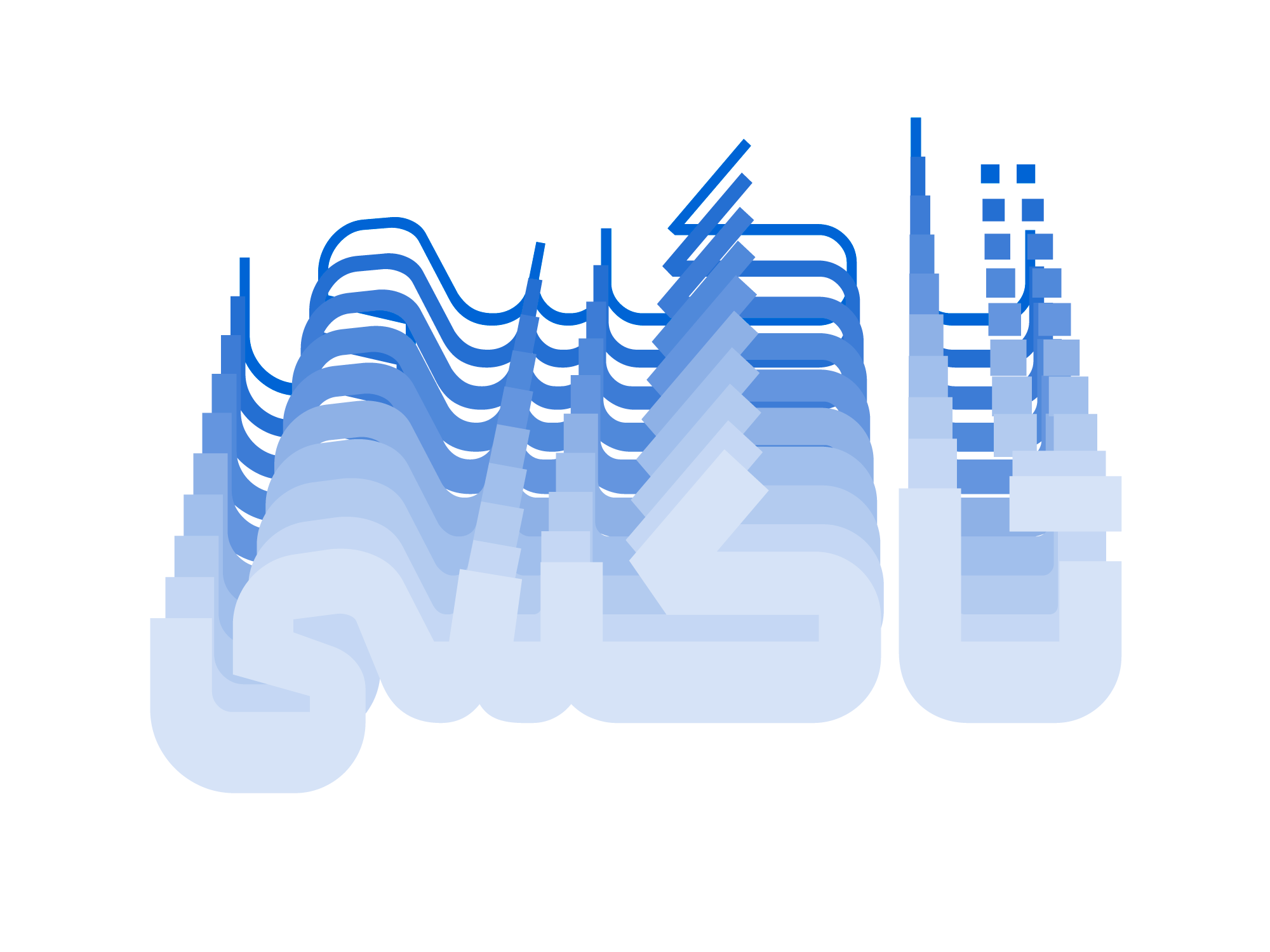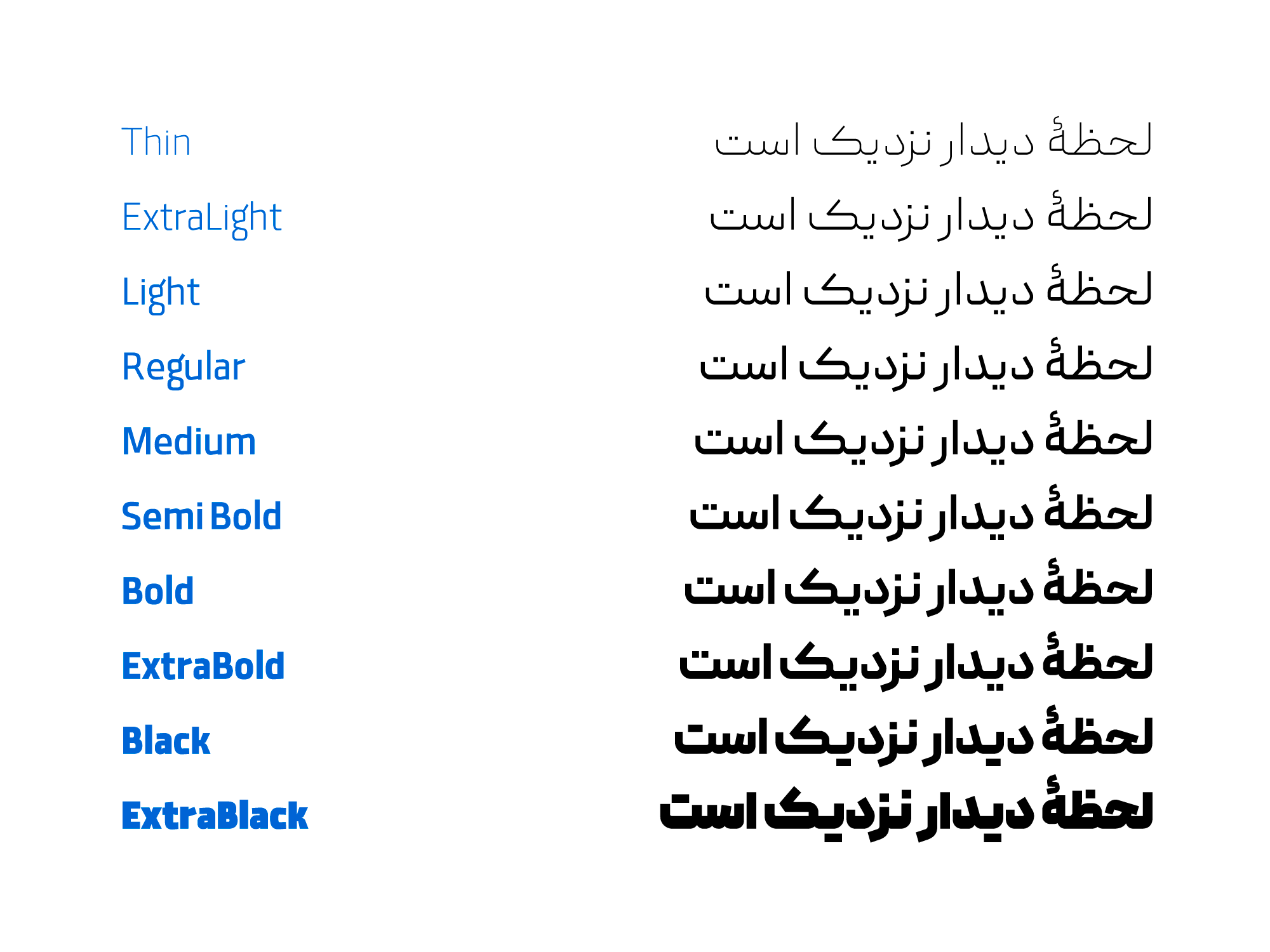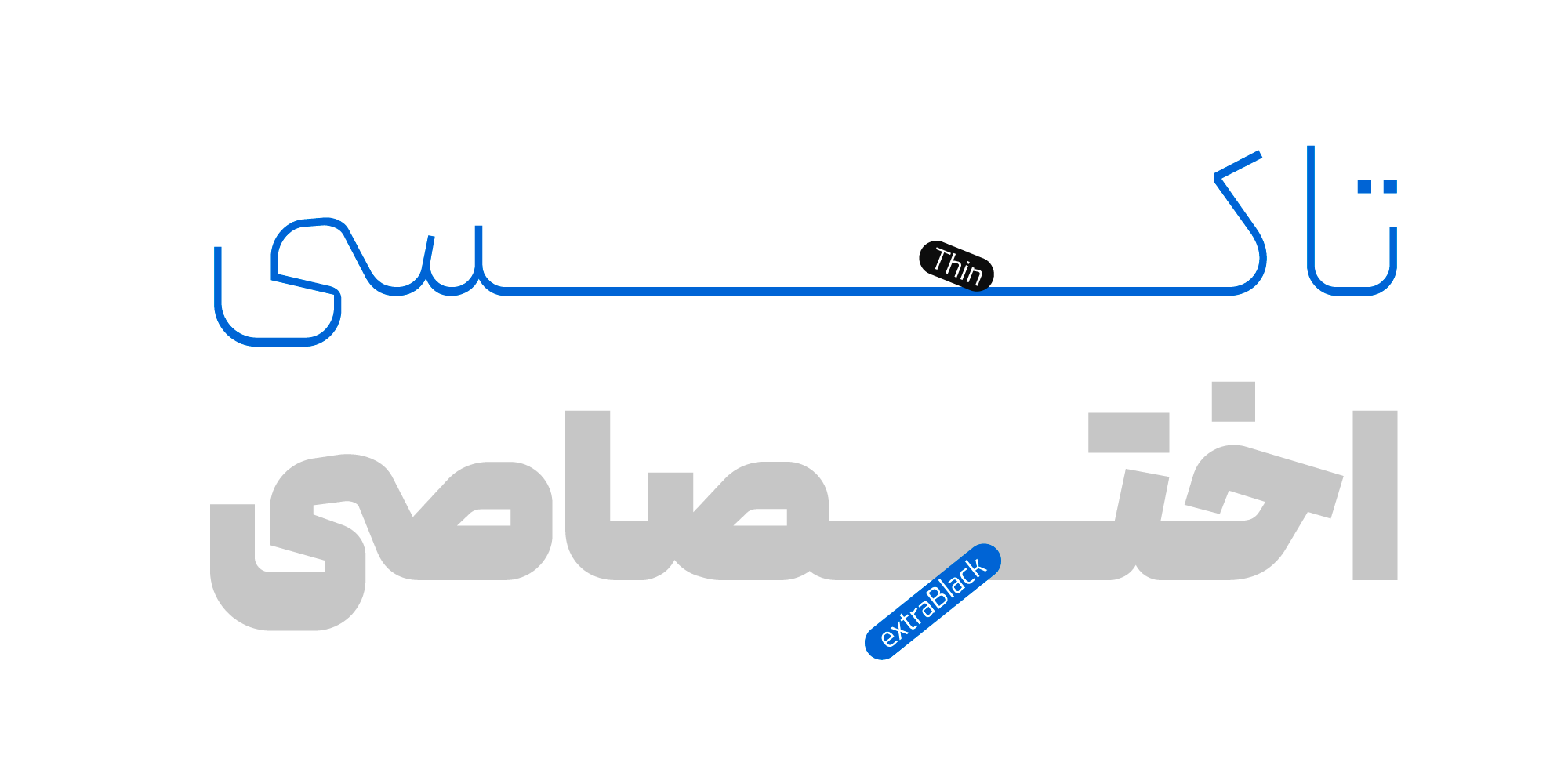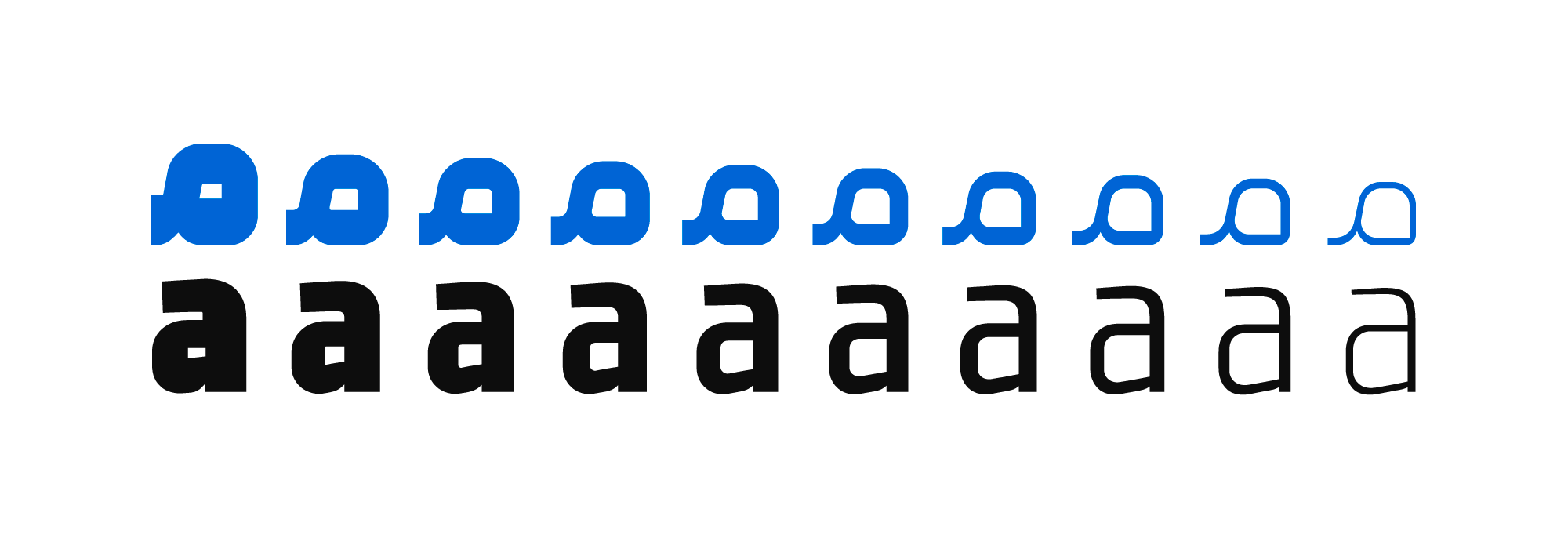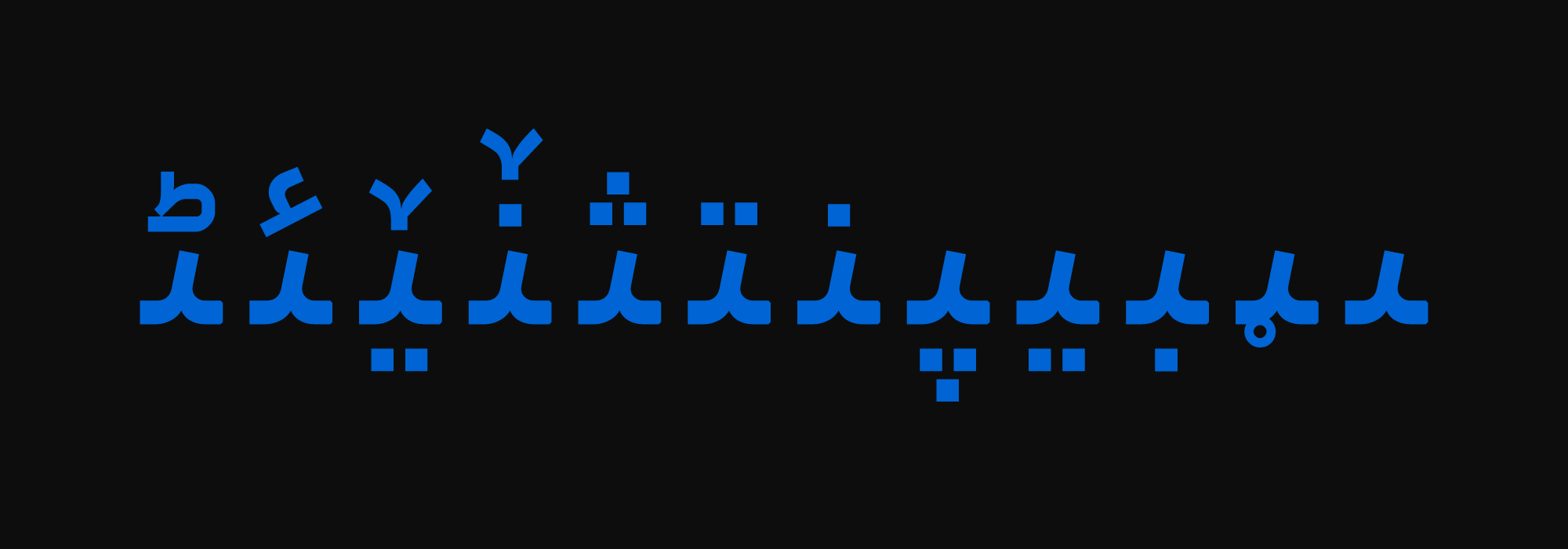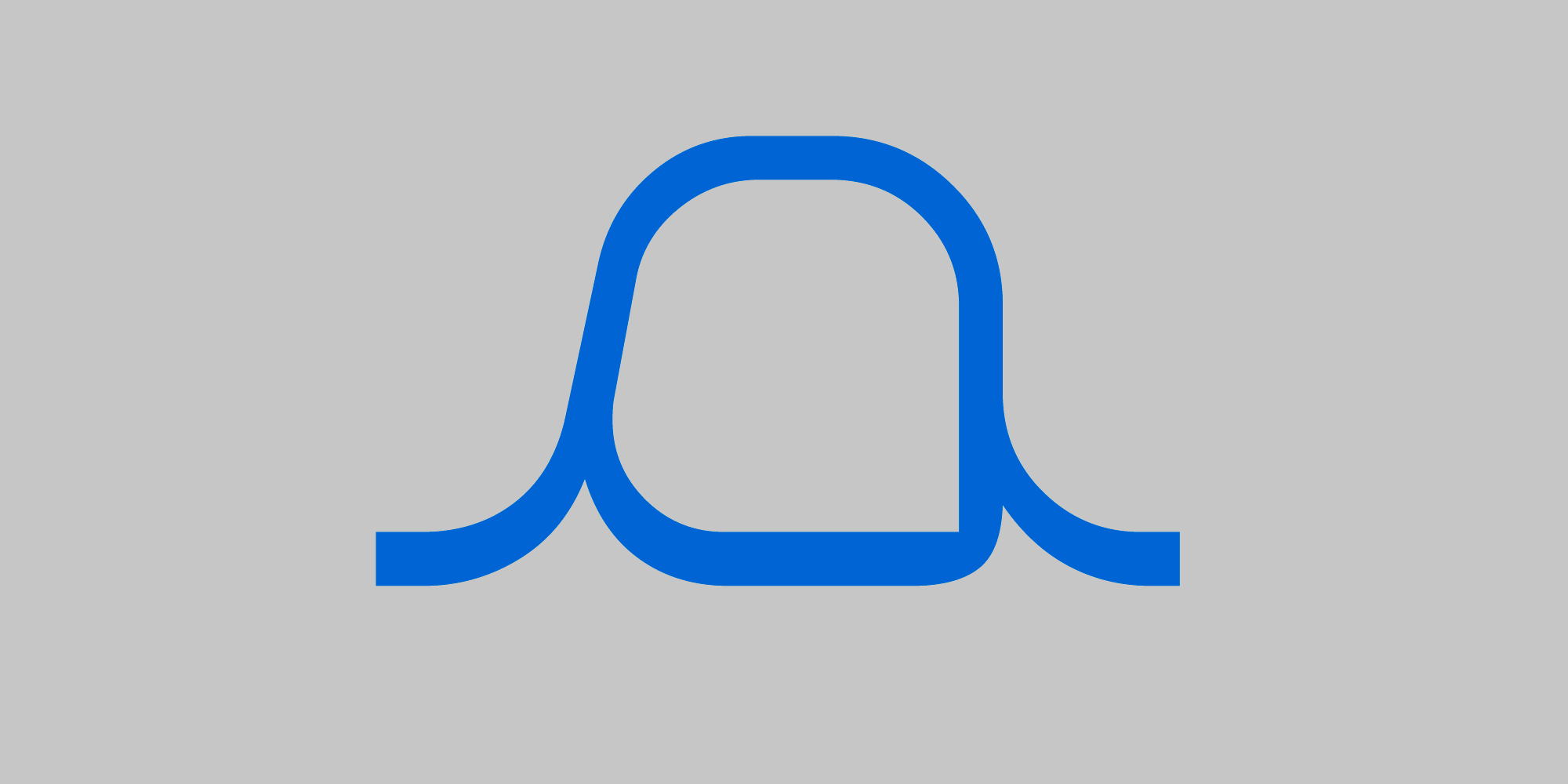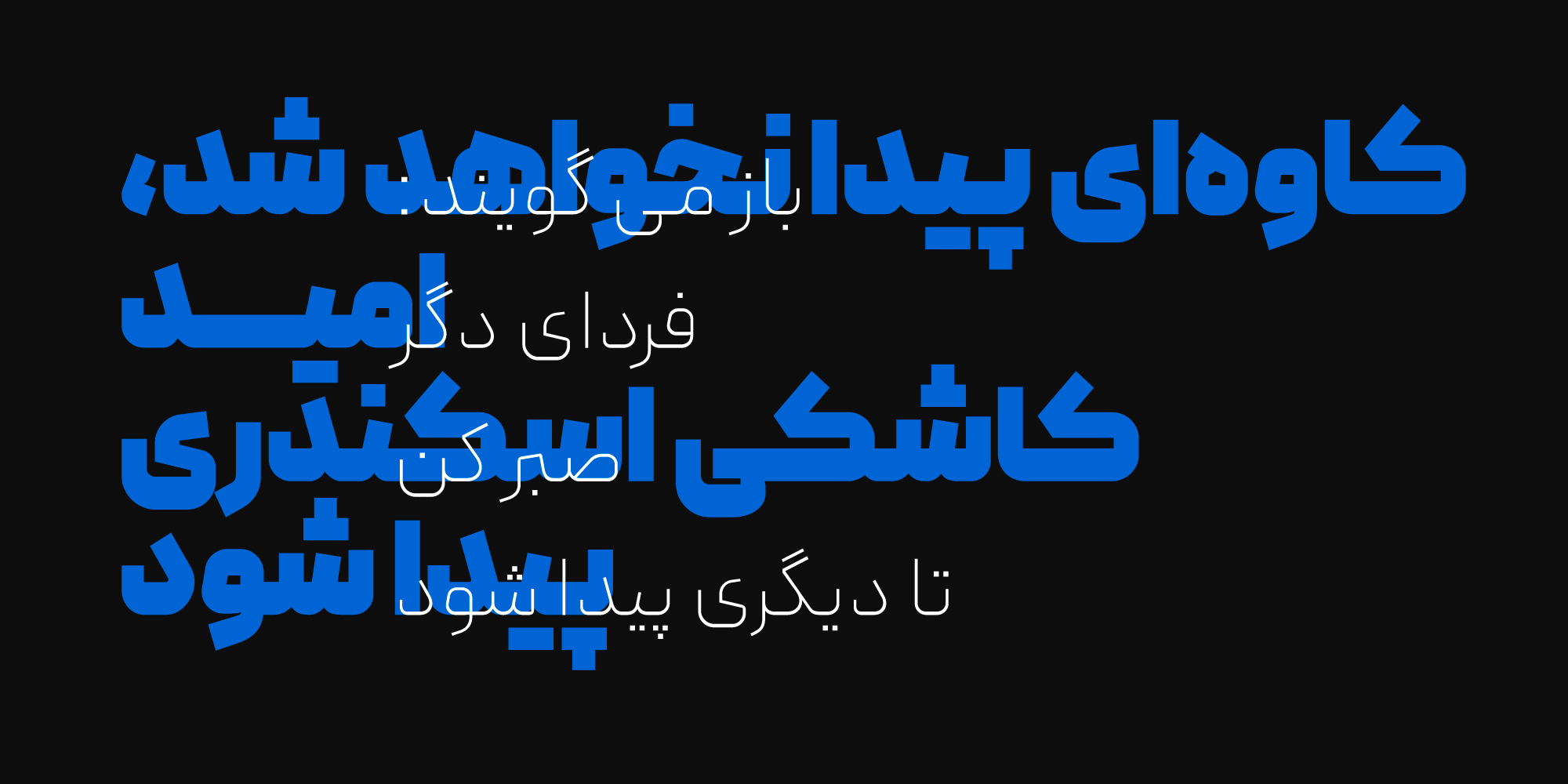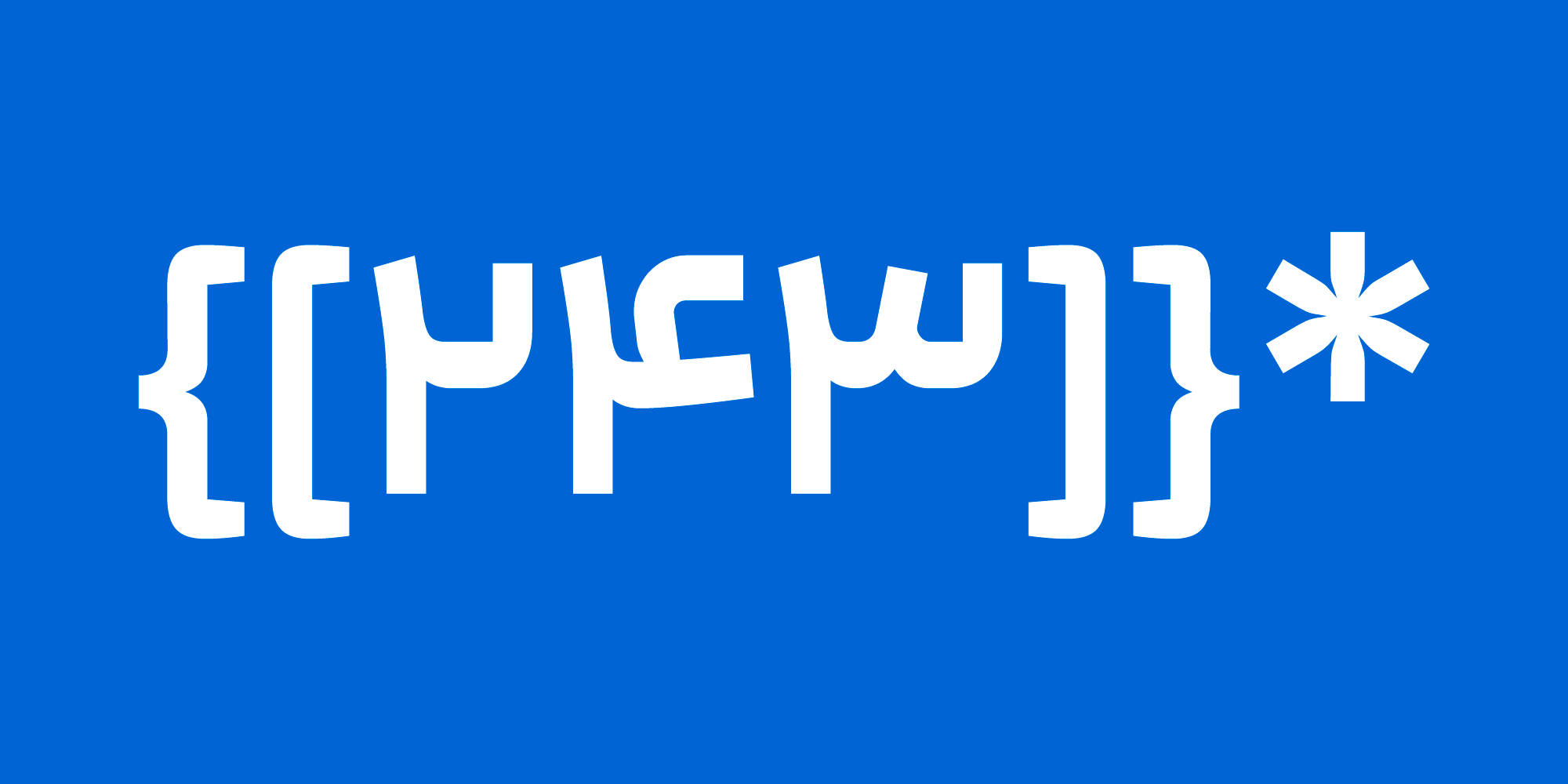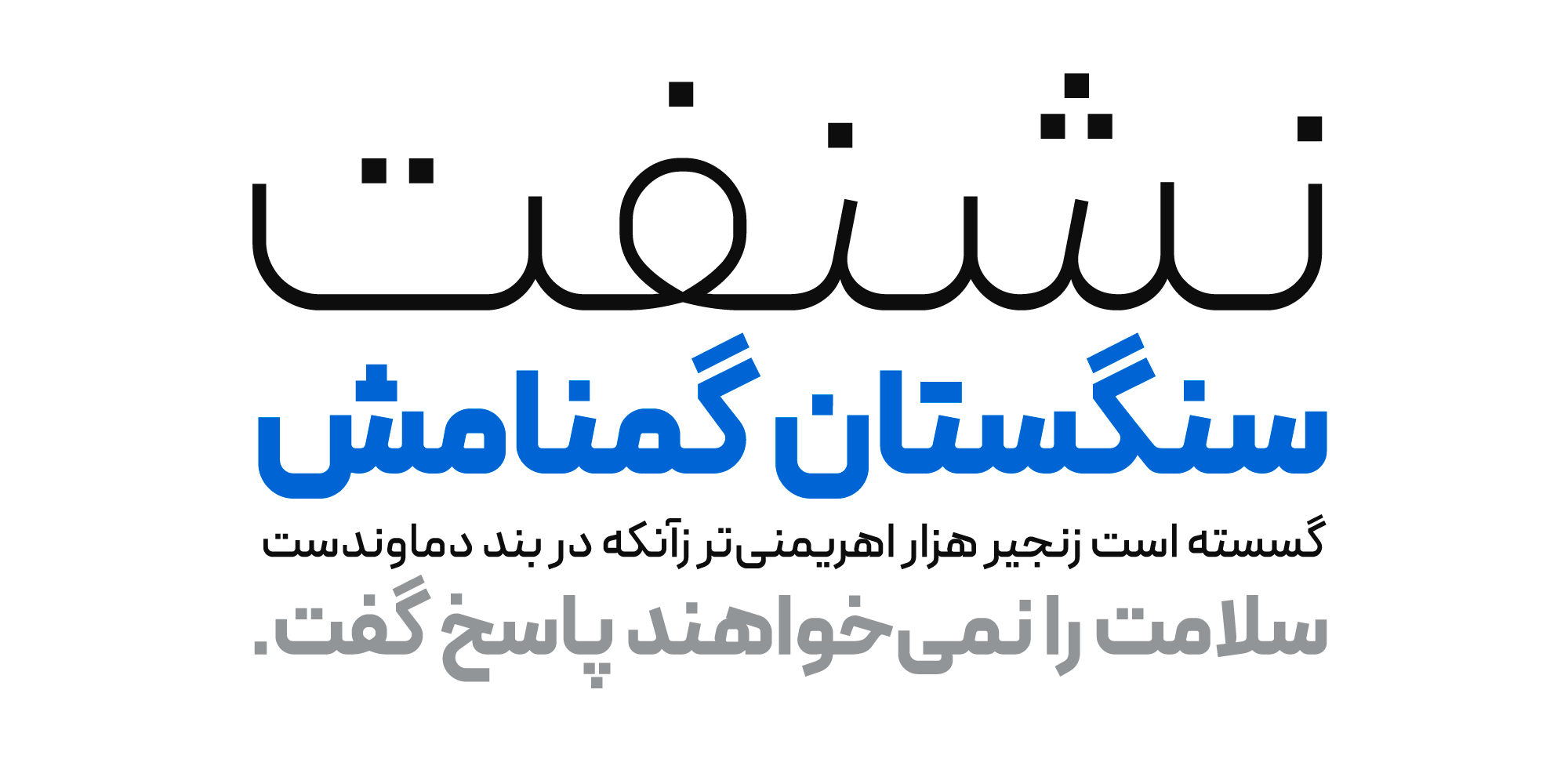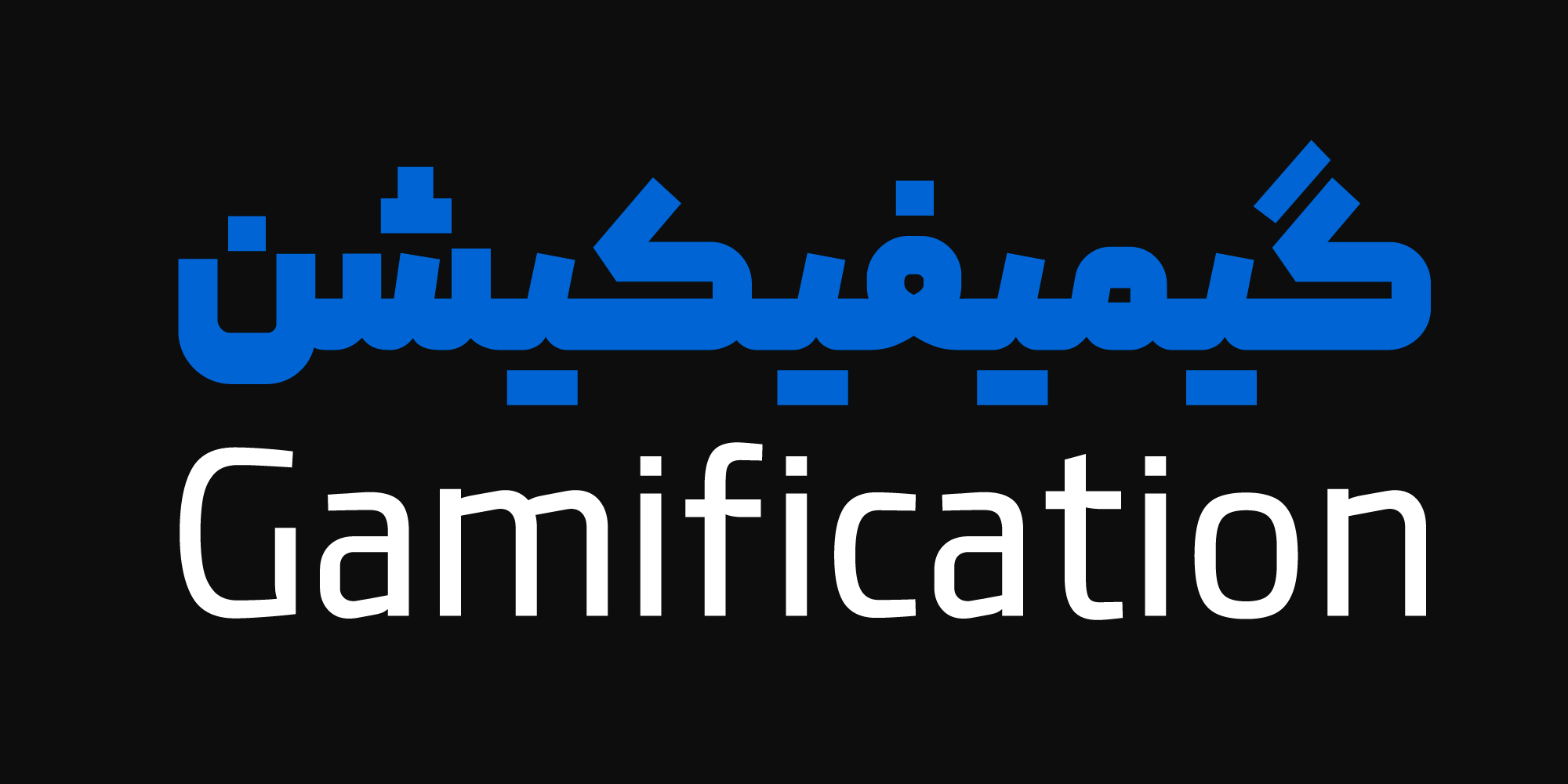
مجموعه ویژگیهای بصری فونت پیدا، آن را به تایپفیسی پرانرژی و برونگرا تبدیل کرده و از همین روی برای استفاده در بیزینسها، استارتاپها و فضاهای الکترونیک مناسب است.
یکی از چالشهایی که در زمانِ طراحیِ این تایپفیس وجود داشت اصرار بر وجود کاراکترهایی با فرمهای بهدور از پیچیدگی است، از همین روی فضایِ چشمِ حروف دارای یک منطق مشخص است و نیز به دلیل استخوانبندیِ مَفصلی و خطوطِ اصلی که عمودی و افقی هستند، کاراکترها فضاهای منفیِ منظمی دارد. «پیدا» روحیهای مدرن دارد و درعین حال میزان قابل قبولی از خوانایی را ارايه میدهد. «پیدا» همچنین برای متنهای کوتاه و نیمه بلند در حوزههای مختلف قابل استفاده است.
ایدهی اولیهی تایپفیس«پیدا» در سال ۱۳۹۸ شکل گرفت، در سال ۱۳۹۹ طراحی نسخه اولیه به پایان رسید و در سال ۱۴۰۴ فونت با رفع ایرادهای فرمی و فنی، اضافه شدن وزن ExtraBlack و نیز تغییراتی در حروف و ترکیبات جایگزین و پشتیبانی از زبانهای کوردی و اردو بهروزرسانی شد.
وزنهای استاندارد
پیدا در بسته حرفهای خود، ۱۰ وزن استاندارد از thin تا ExtraBlack را دارد که برای کاربردهای متنوع – از صنعت چاپ تا فضاهای مجازی – درنظر گرفته شده است. خانواده فونت پیدا برای استفاده در فضاهای وب نیز بهینهسازی شده است و فایلهای مورد نیاز در کنار فایلهای اصلی قرار داده شده است.
وریبل فونت
فونت پیدا -در نسخه چهارم خود- به صورت وریبلفونت ارایه شده است که علاوه بر ایجاد دسترسی به وزنهای میانی بین وزنهای استاندارد، تمام وزنها در قالب یک فایل فونت را در دسترس قرار میدهد.
پشتیبانی از زبانهای انگلیسی، عربی، کردی و اردو
تایپفیس پیدا برای زبان فارسی و لاتین طراحی شده است و زبانهای عربی، کوردی و اردو را پشتیبانی میکند.
حروف و ترکیبات جایگزین
برای ایجاد تنوع در شیوه نگارش و خوانایی، جایگزینهایی برای بعضی از حروف و نیز چند ترکیبِ جایگزین دوتایی مشخص شدهاند.
در فونت «پیدا» برای حروف «ی»، «ئ» و «ي» حرف جایگزین طراحی شده است. این حروف جایگزین در دسته Stylistic Alternates قرار دارند که به صورت Stylistic Set (Set01) نیز در دسترس هستند.
همچنین حالت کشیده (جایگزین) حرف «ک» و «گ» در دسته Swash قرار دارد.
ترکیبهای دوحرفیِ جایگزین که به حرف «ی»، «ر» و «ن» ختم میشوند و همچنین نمادهای ریال و تومان بهصورت لیگیچرهای Discretionary Ligaturesدر دسترس هستند.